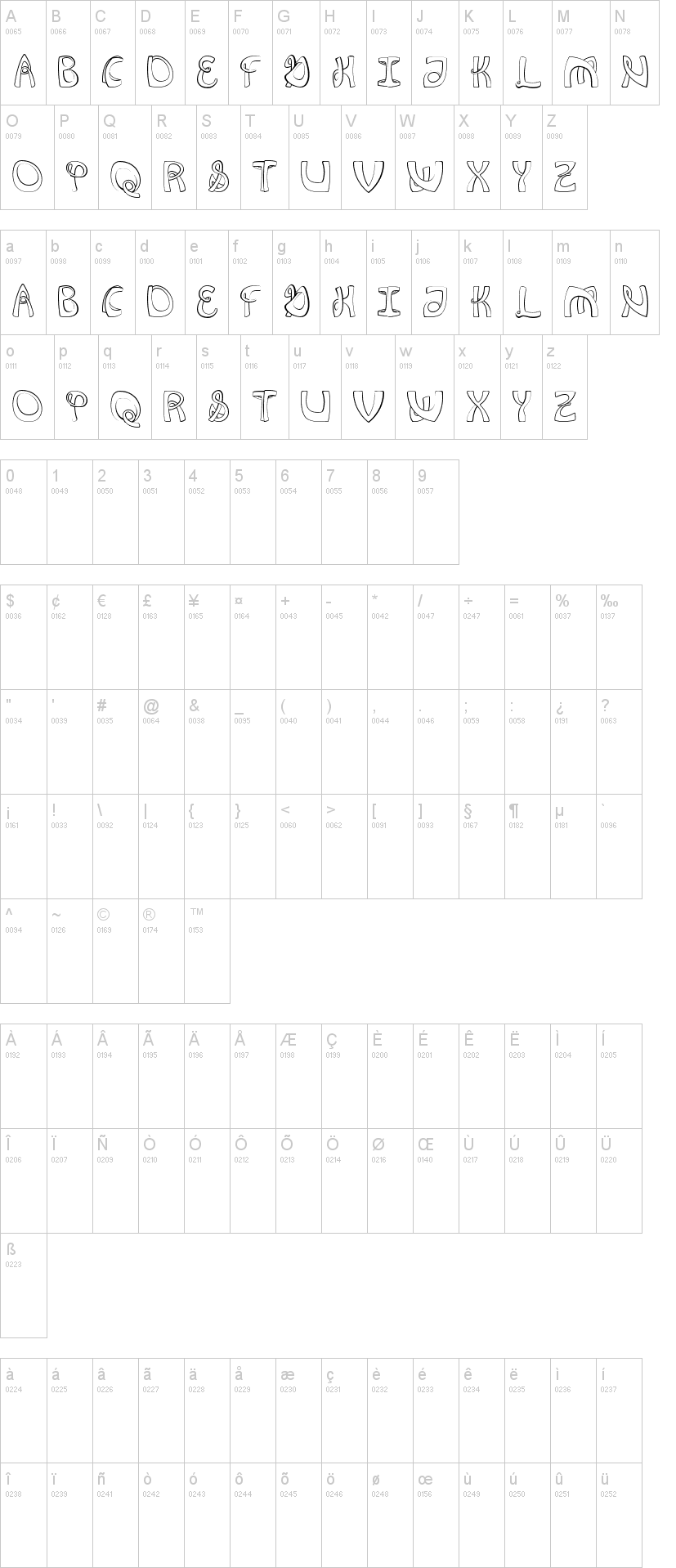
Flexion
Flexion 字体是一款专为设计师和开发者设计的字体。它由一系列细节丰富的字体来支持视觉设计,以及更加灵活的字体调整和组合。Flexion 字体拥有大量的字体变体,可以满足不同的文字需求,使用者可以轻松地调整字体的尺寸、颜色、对齐方式等。它还支持多种语言,可以让用户在不同语言环境中使用。
Flexion是一款非常不错的手写艺术字体,具有很好的视觉感,适合于文化类的宣传设计、商业类品牌的广告和产品包装设计以及个性化文字排版等较多场景。
Flexion字符映射图